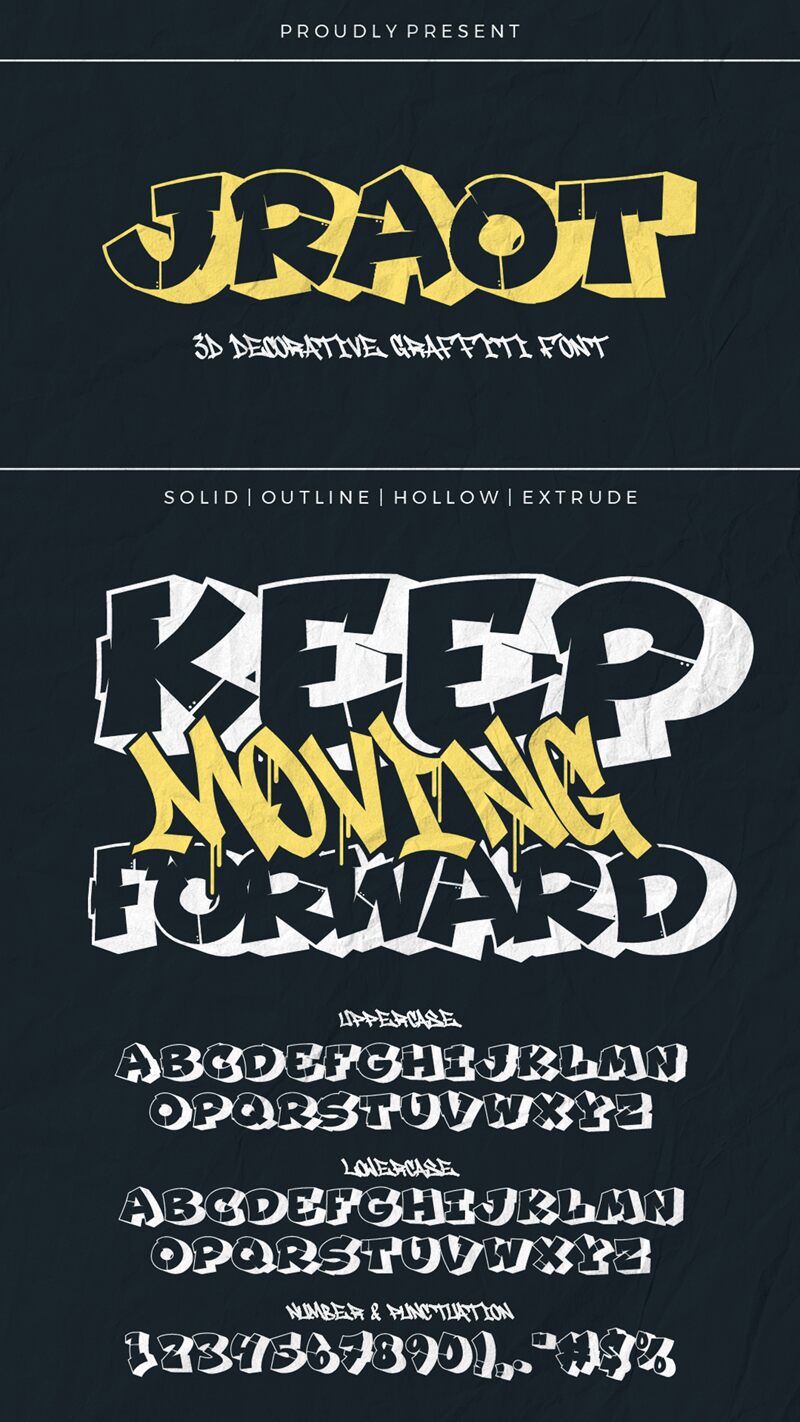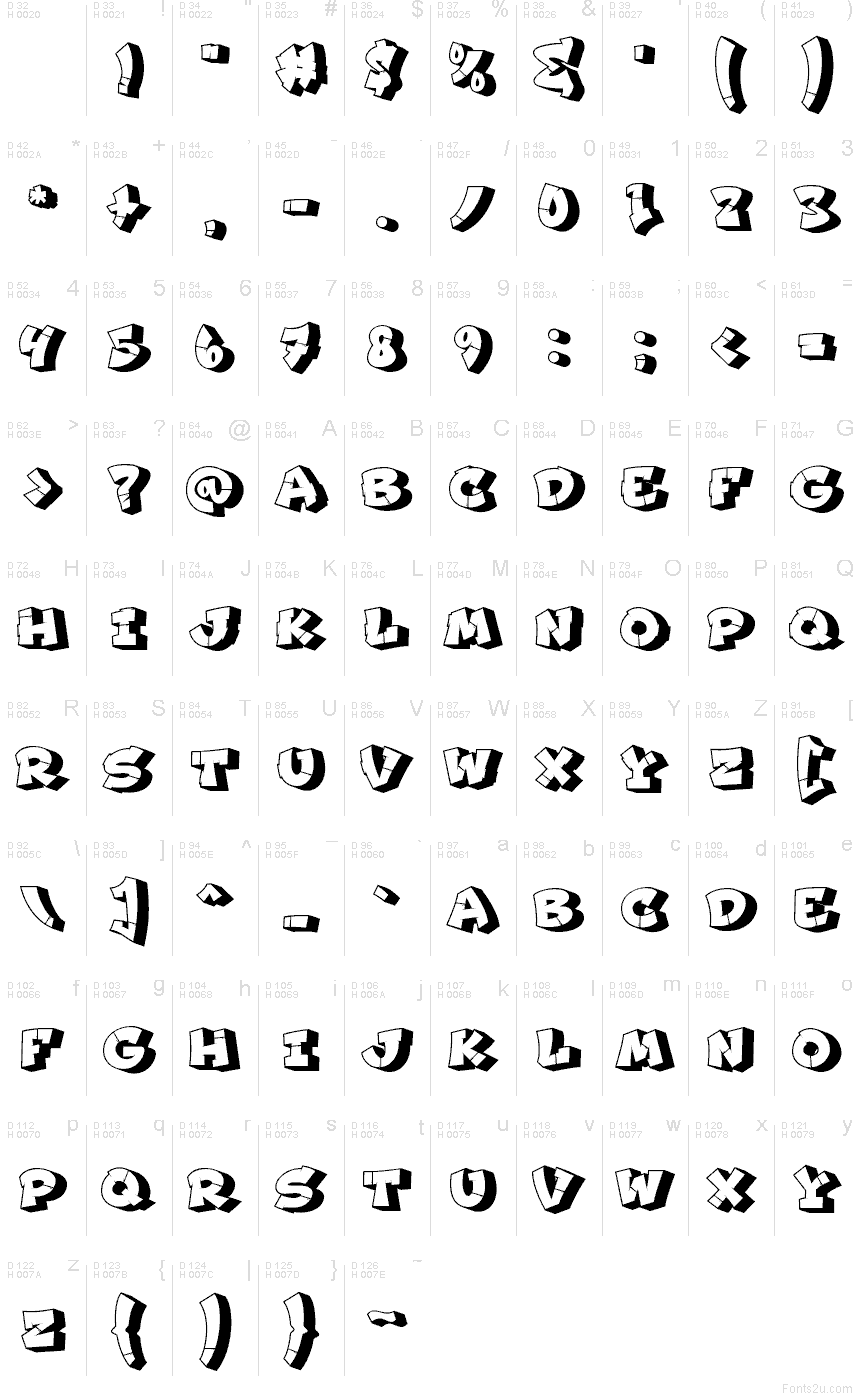
Jraot Hollow od Sipanji x Cikareotype je bezplatné komiksové písmo typu display. Díky nakloněným blokovým siluetám a nadrozměrným černým stínům působí písmena jako vystřižená nebo nalepená na plakát. Zatímco vnitřky písmen zůstávají čistě bílé, výrazná spodní vrstva dodává designu ten správný kreslený říz.
Tato hloubka skvěle vynikne v náhledech na YouTube, názvech her, letácích na dětské akce, na nálepkách nebo plakátech v komiksovém stylu, kde krátká slova potřebují silný grafický prvek. Písmo se skvěle hodí i na potisky merche či obaly – zejména pokud hledáte pořádně tučné písmo, které působí energicky a hravě, nikoli formálně.